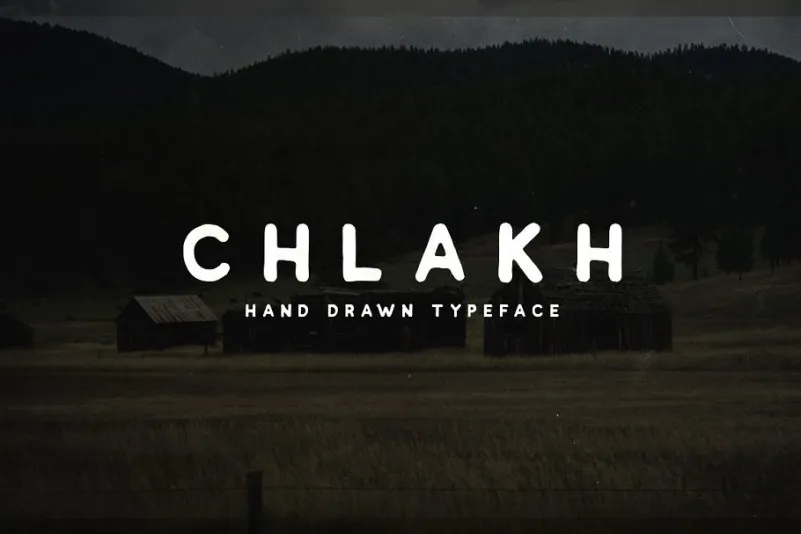
A fonte Chlakh – Hand Drawn Font é uma seleção perfeita para quem busca um toque retro em seus projetos. Esta font se destaca por seu design original e combinatória de caracteres únicos que criam um visual atualizado, adequando-se bem à categoria de fonts vintage retro. Ideal tanto para a criação de logotipos, como para outras aplicações mais cotidianas como etiquetas em embalagens de alimentos, cartões de negócios, folhetos e outdoors. Seu design cuidadosamente pensado faz com que Chlakh se torne uma escolha excelente não apenas para personalizar seus produtos de retalho vintage, mas também para qualquer projeto gráfico moderno. Para aqueles que buscam um equilíbrio perfeito entre o vintage e a contemporaneidade na sua identidade visual, Chlakh é uma ótima adição. Desenvolvida por Roman Paslavsky, esta font foi criada como uma complementação para a linha de produtos antigos do designer. A simplicidade elegante e a personalização única da letra garantem que o uso desta font se destaque em qualquer aplicação gráfica. Convidamos você a explorar suas possibilidades ao criar logotipos vintage, designs de adesivos ou até mesmo texturas para sua próxima camiseta. Chlakh é uma ferramenta versátil e criativa que certamente encaixará perfeitamente em qualquer projeto gráfico da categoria retro do seu negócio.